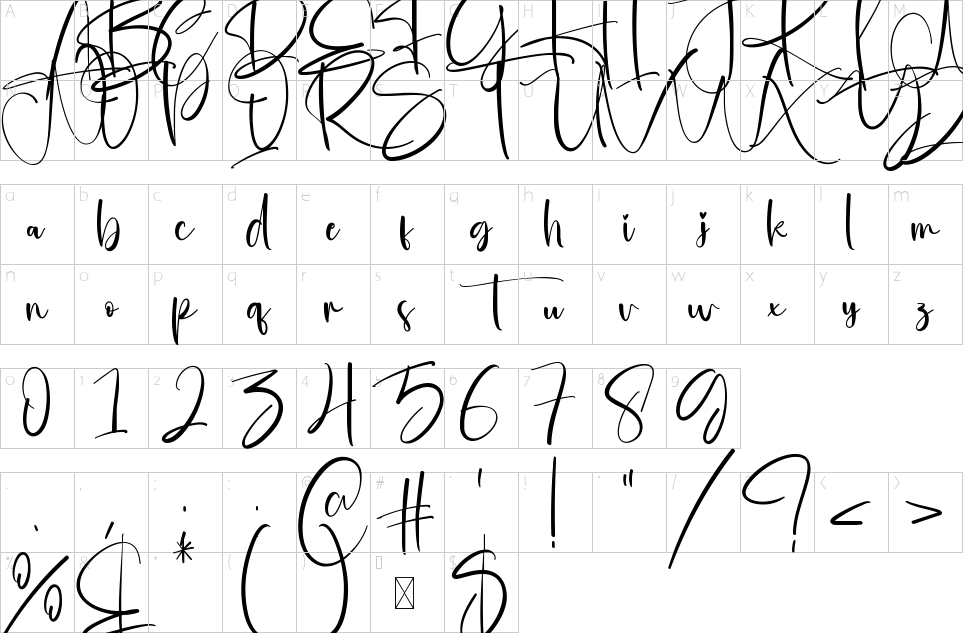
Descubra a essência da Astone, uma fonte de design simples e elegante criada por scratchones. Com linhas finas e tipografia minimalista, Astone oferece uma experiência visual harmônica para qualquer projeto. Seja para aplicativos de desktop, websites ou materiais de impressão, a Astone font é a escolha perfeita para quem busca um look moderno e sofisticado. Esta fonte foi desenhada pensando em sua facilidade de uso e em sua capacidade de combinar bem em diversos contextos. Descubra por si mesmo o charme e a versatilidade desta fonte gratuita para Windows e Mac, e experimente o design de alta qualidade que Astone tem a oferecer.